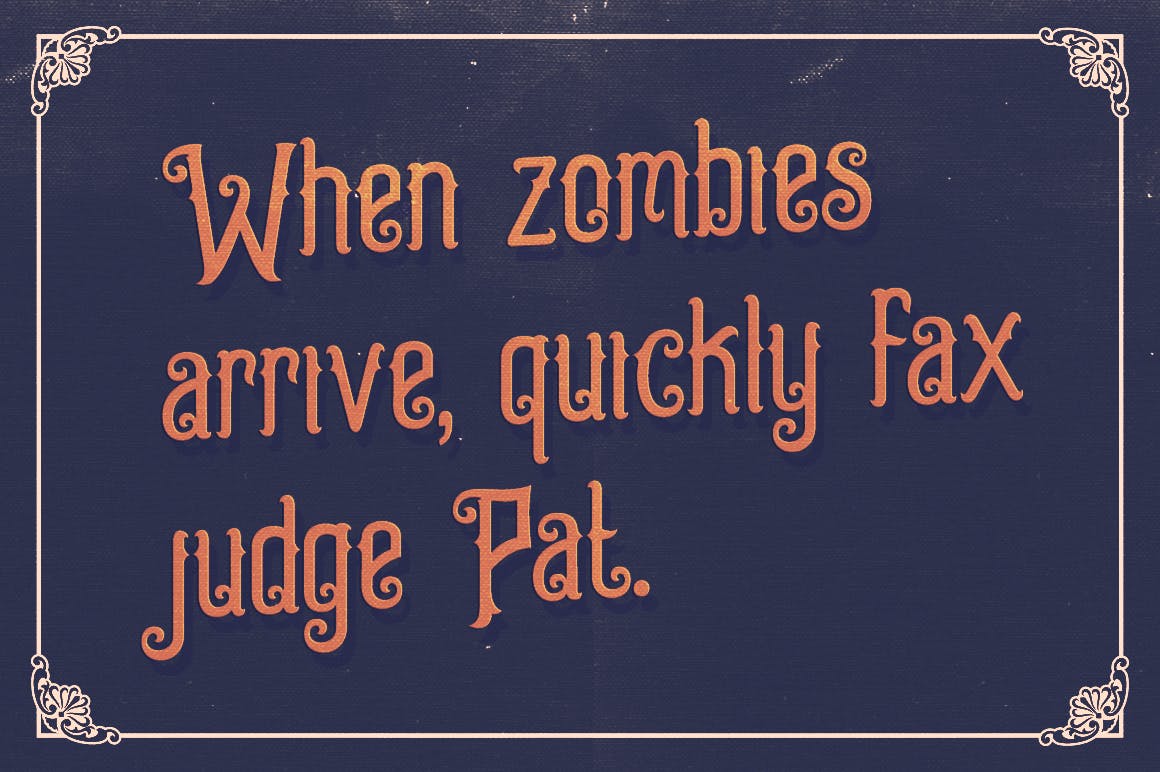
Mermaid Typeface
فونت مرمید با الهام از سبک‌های ویکتوریایی، گزینه‌ای ایده‌آل برای پروژه‌های طراحی شماست.
فونت مرمید یک فونت قدیمی و با سبک‌های ویکتوریایی و زینتی الهام گرفته شده است. این فونت شامل نسخه‌ای برای وب است، بنابراین می‌توانید از آن برای طراحی وبسایت‌ها استفاده کنید.